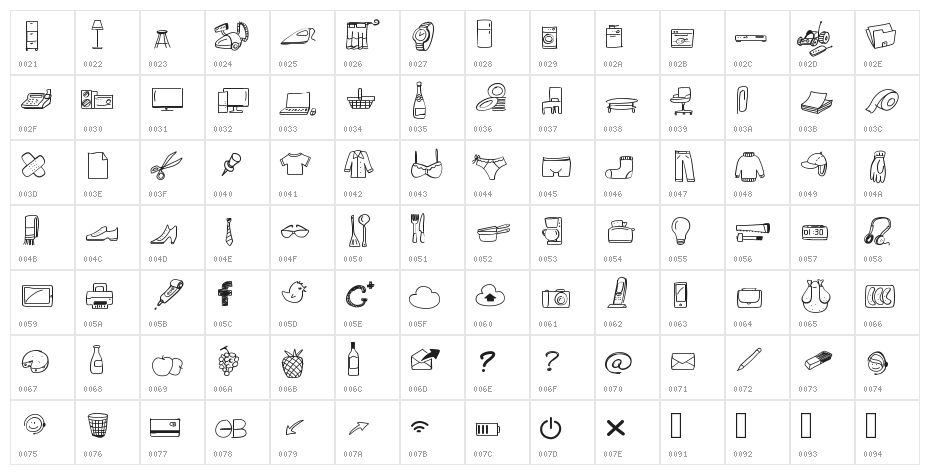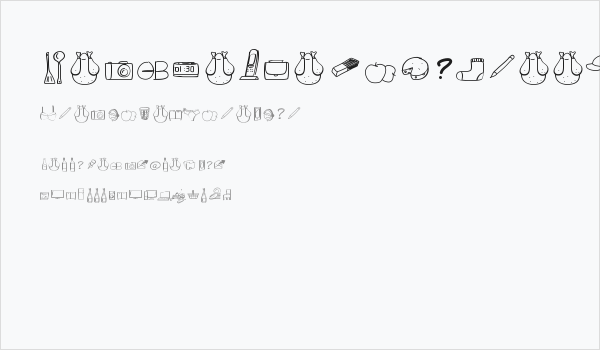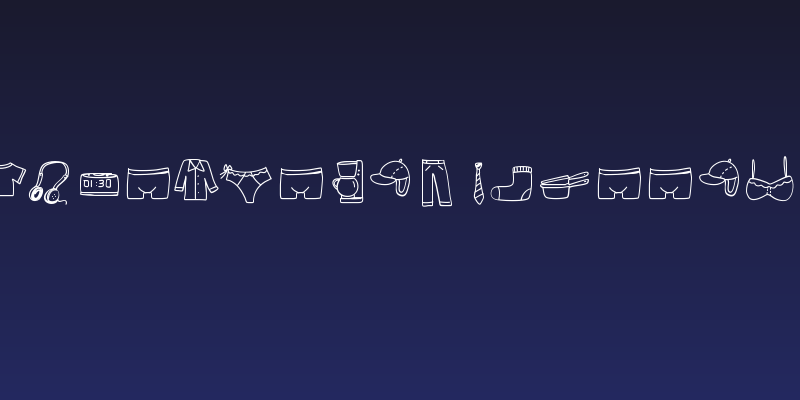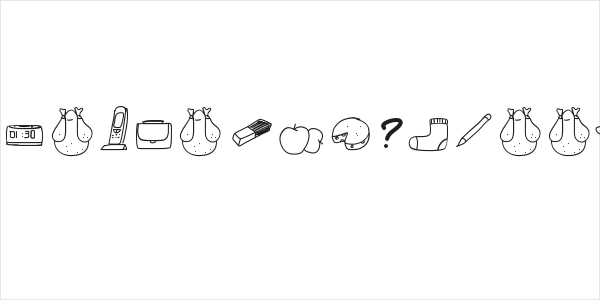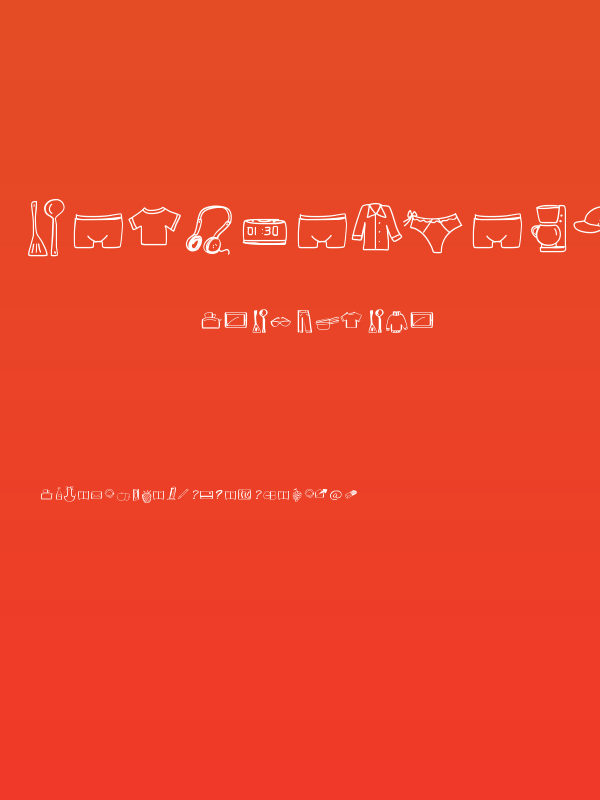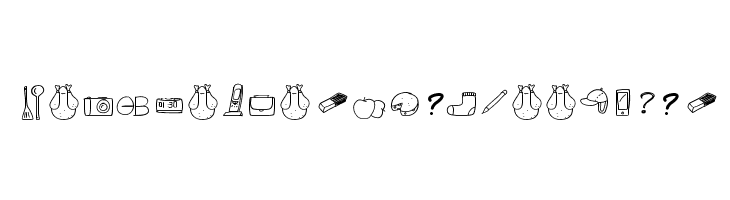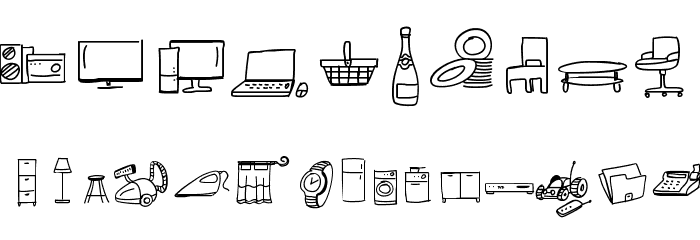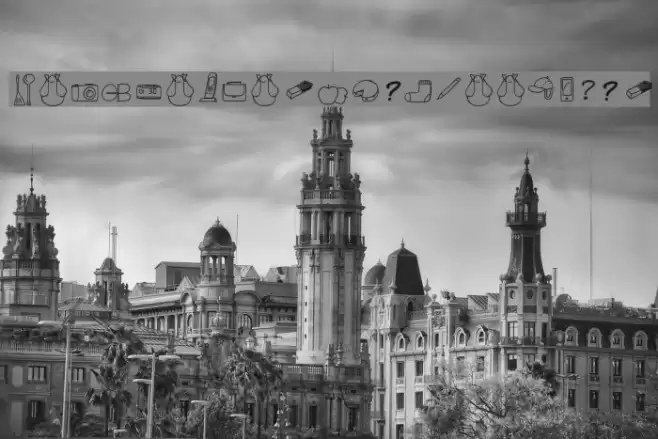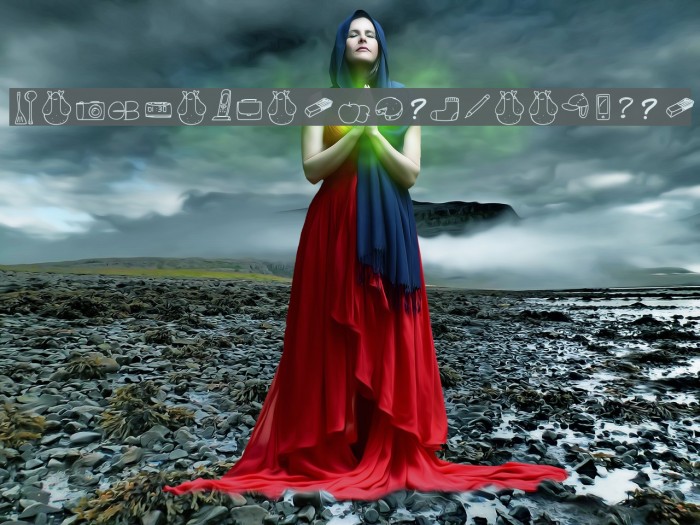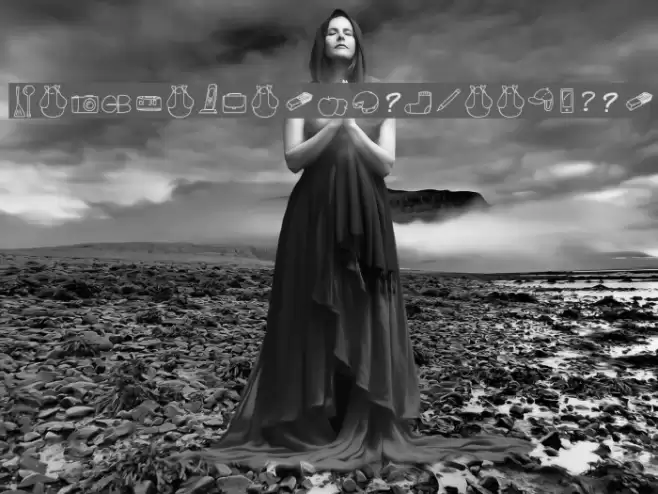
PeaxWebdesignFreeIcons Font
| Общий стиль | Decorative, Playful, Hand-drawn |
| Область применения | Icons, UI elements, Illustrations |
| Рекомендуемые проекты | Web design, mobile apps, infographics, educational materials, children's content, casual branding. |